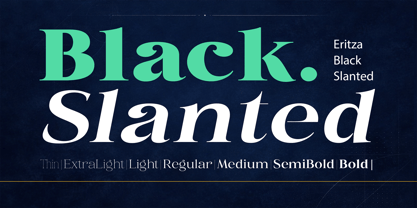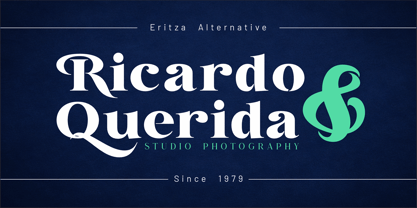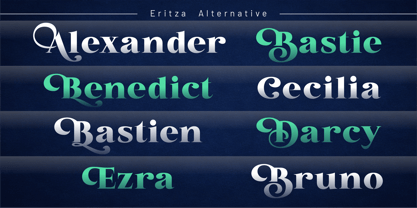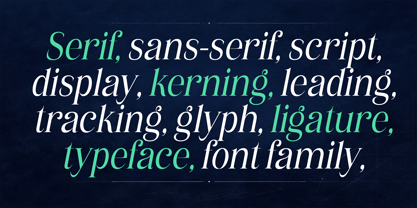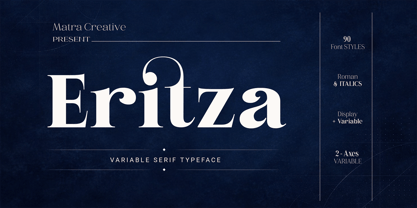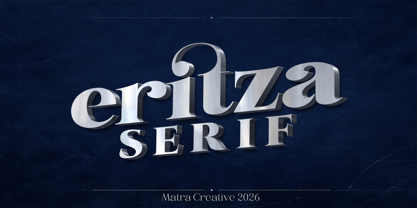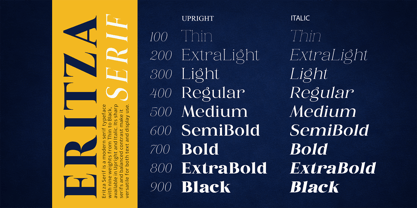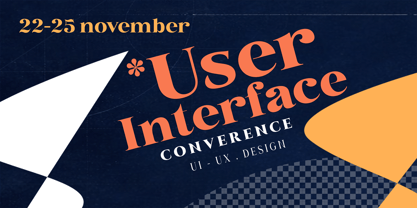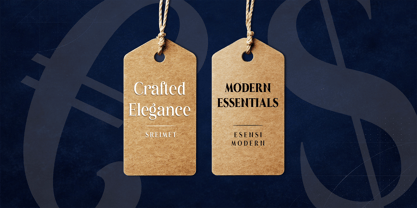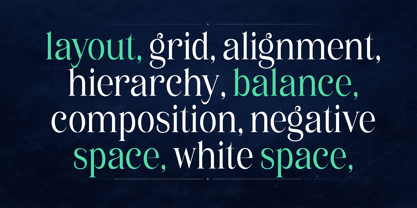
Eritza
von Matra Creative
Die Schriftfamilie Eritza wurde von May Adifarzan muis entworfen und von Matra Creative veröffentlicht. Eritza enthält 89 Stile und Familienpaketoptionen. Mehr über diese Familie
Timeless Serif Typeface is a refined serif font that merges classic elegance with modern precision, crafted with balance and sophistication to suit premium branding, editorial layouts, and distinguished design projects, while Eritza Variable Serif Typeface by Matra Creative expands this refinement into versatility with 90 styles in Roman and Italics, offering both display and variable options across two axes of variation, making it highly adaptable for designers who seek flexibility without losing elegance—together, these typefaces embody timeless artistry and modern adaptability, perfect for luxury branding and editorial excellence.
Designer: May Adifarzan muis
Aktuelle Foundry: Matra Creative